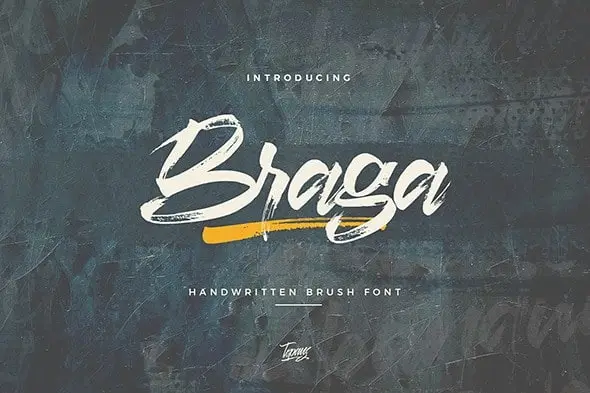
Braga Brush Font – Download Grátis
Braga Brush Font é uma tipografia de escrita com traços de esférico que oferece estilo claro e movimento dramático. Este tipo de letra é perfeitamente adequado para seus próximos projetos criativos, como logotipos, cartões personalizados, cartas de encargo, embalagens de produtos, cabeçalhos e até mesmo roupas. A sua natureza dinâmica faz com que Braga Brush seja uma fonte ideal para incorporar um elemento único e atraente em uma variedade de ambientes gráficos. Seja você designer ou artista, esta fonte de traço esférico é o tipo perfeito para trazer vida à sua próxima peça visual.